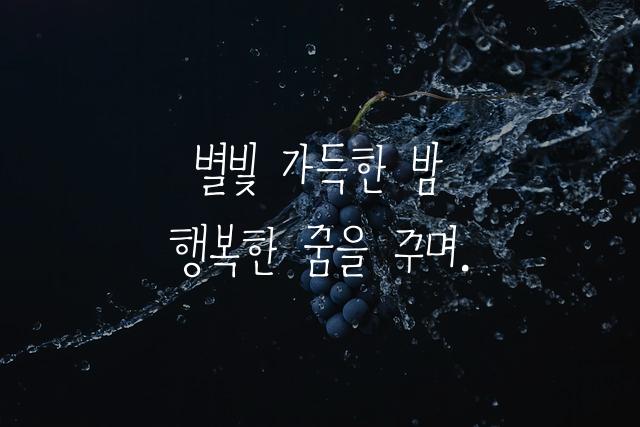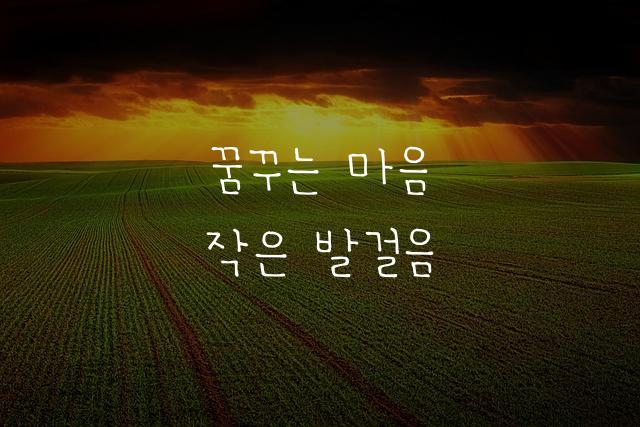
ACC 어린이 가을담은체는 국립아시아문화전당이 제작한 폰트로, 각진 손글씨와 키가 큰 특성을 지닌 펜 스타일의 글꼴입니다. 또박또박한 질감이 감성적인 표현을 더욱 돋보이게 합니다.
ACC 어린이 가을담은체은(는)
손글씨, 두꺼운 스타일, 펜/붓터치, 네모꼴, 감성적인, 단단함, 길고/크고 계열의 생김새를 가지고 있으며
어린이 책, 초대장 등에서 자주 활용되며, 효과적인 메시지 전달에 적합합니다.
이 폰트는 교육, 유아/가족 분야에 잘 어울리며,
귀여운, 편안한 느낌을 담고 있는 것이 특징입니다.